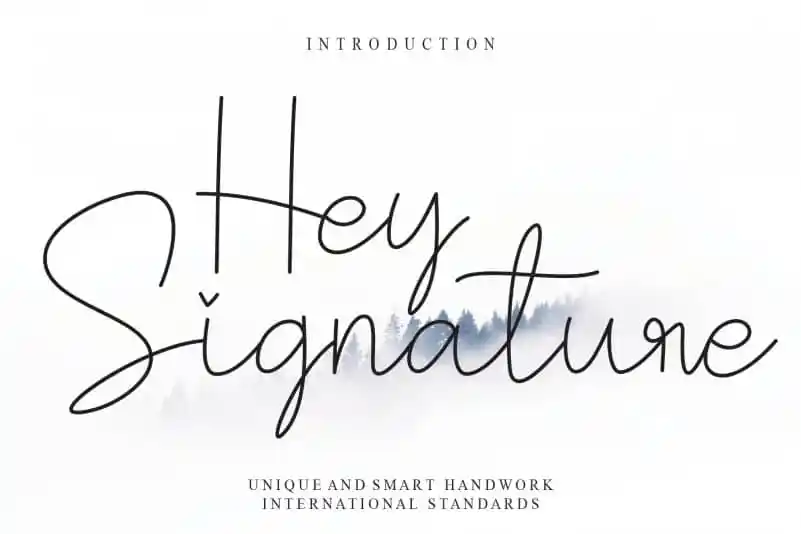
Hey Signature Handwritten Font – Fonte Grátis
Hey Signature Handwritten Font
Esta página de download apresenta a Hey Signature Handwritten Font, uma fonte original criada pelo designer creativeletter. Com traços delicados e uma caligrafia natural, esta fonte é perfeita para quem busca um toque especial em suas criações digitais. Ideal para designers que valorizam o encanto visual de uma autêntica escrita a mão, essa fonte oferece a sensação de serenidade e criatividade. Suas linhas suaves e traços arredondados adicionam um toque acolhedor ao seu design, sem perder a precisão necessária para um uso profissional. Perfeita para aplicar em títulos, listas e detalhes em seus projetos gráficos, Hey Signature Handwritten é uma escolha inteligente para aqueles que desejam adicionar personalidade e originalidade ao seu trabalho. Seja você designer de moda ou artista digital, essa fonte oferece a oportunidade de criar algo único e impactante. Adicione um toque autêntico à sua próxima criação com a Hey Signature Handwritten Font do creativeletter.